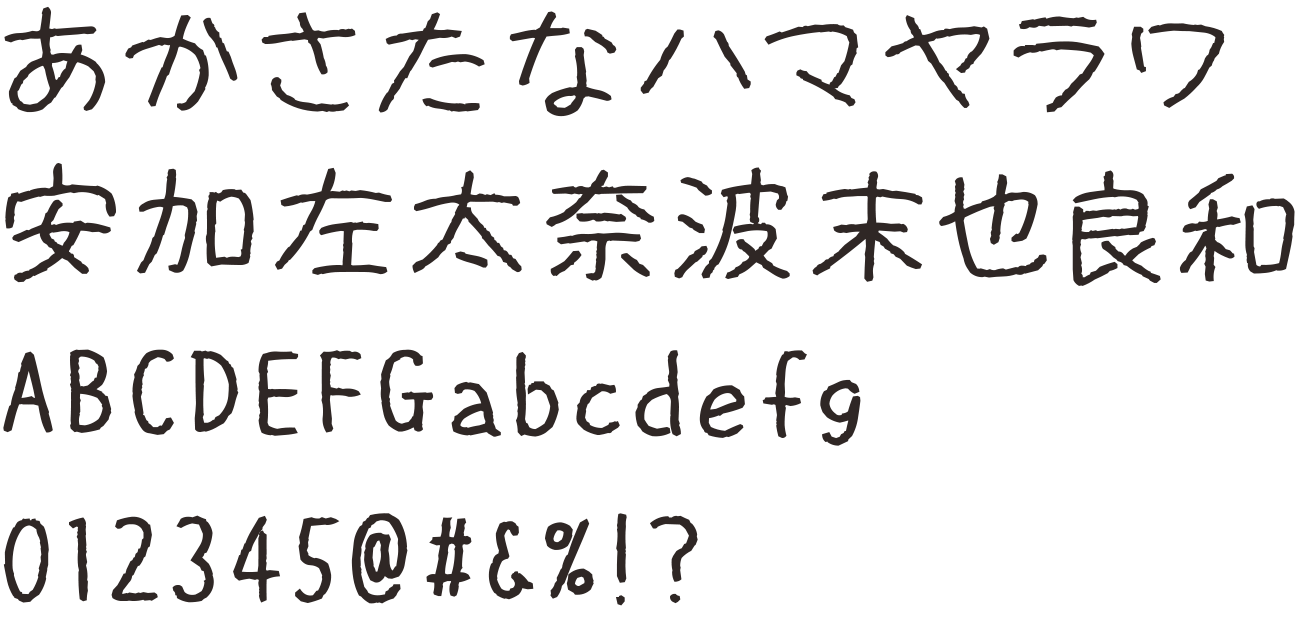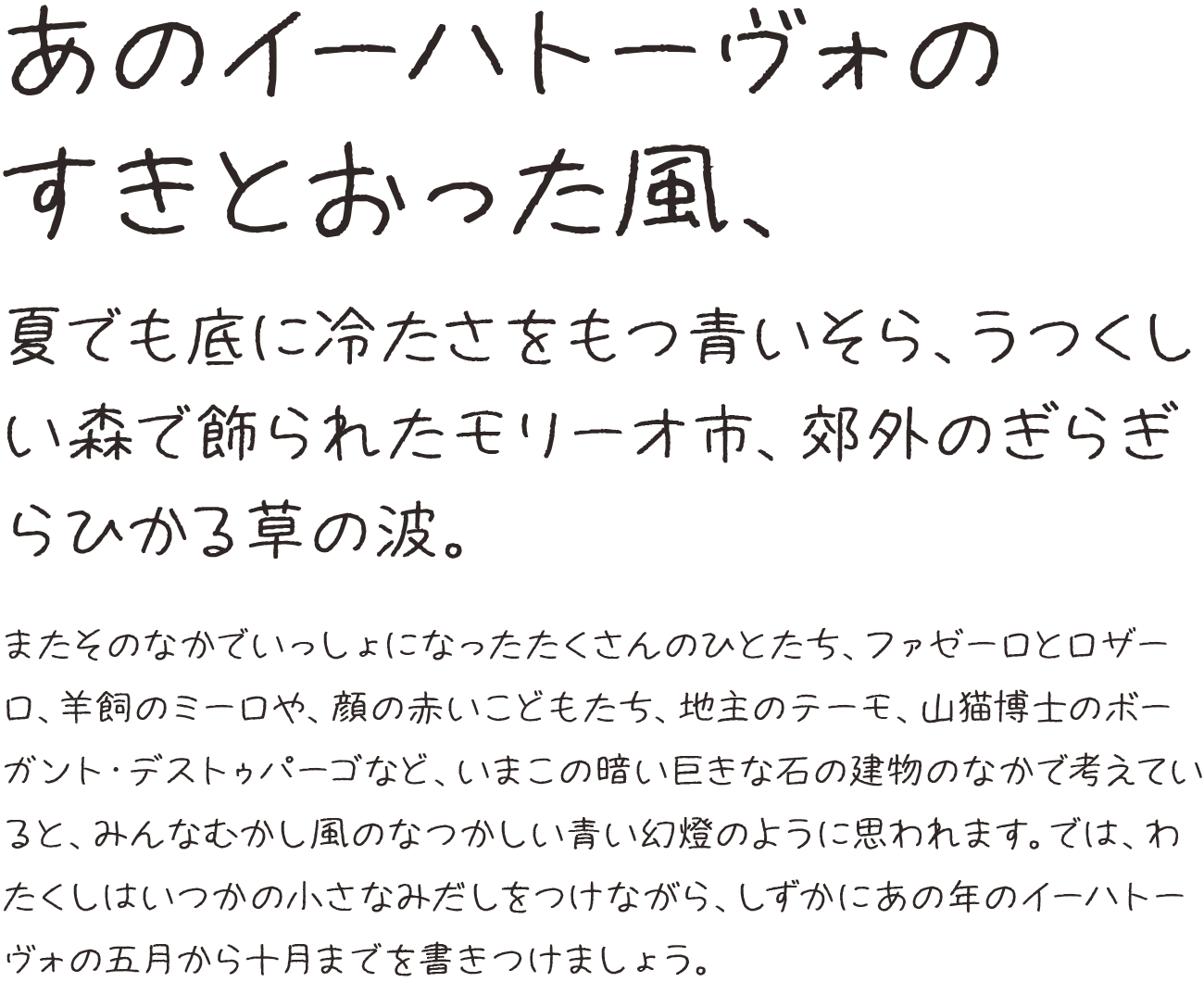
ねこのけフォント(夏) Bold
夏に向けてすっきりする猫の毛並みをイメージして制作された、細めでさらっとした手書きフォント。7,465字収録・2ウエイトのセットで、BOOTHで購入すると同テイストの素材60点も同梱。
まんまると太めの「ねこのけフォント(冬)」と組み合わせて使うのもおすすめ!
ねこのけフォント(夏) Boldの組見本